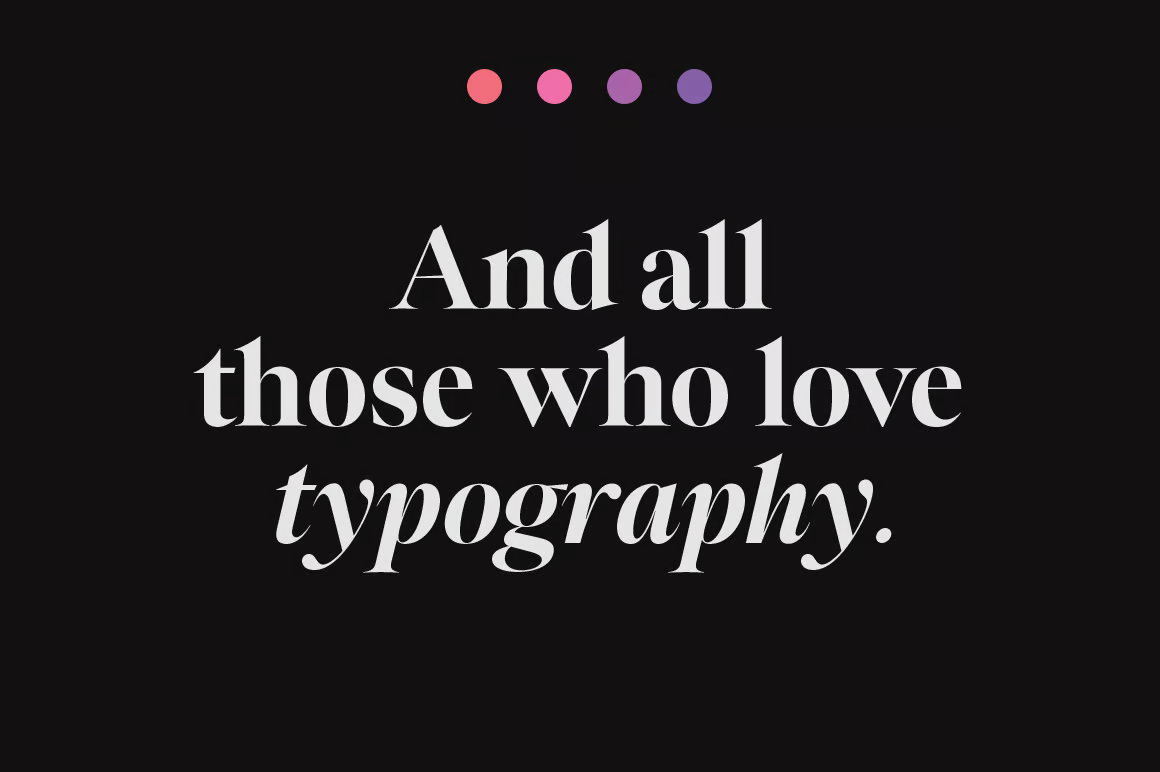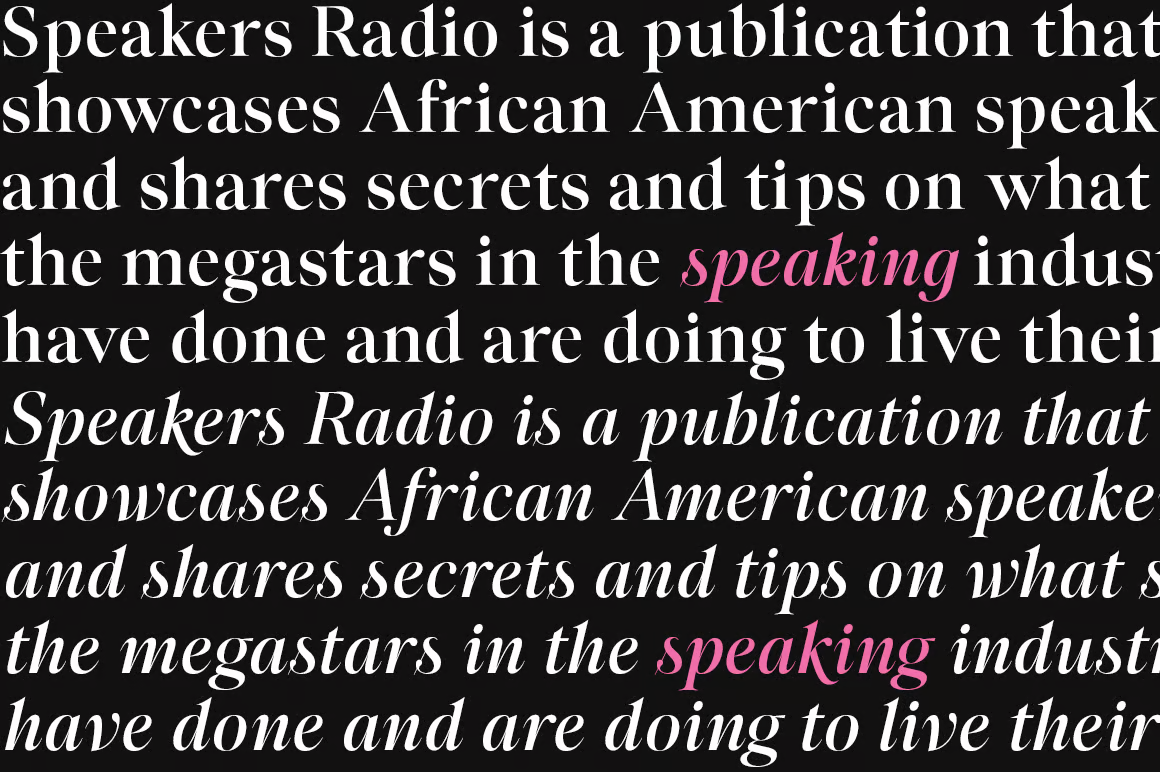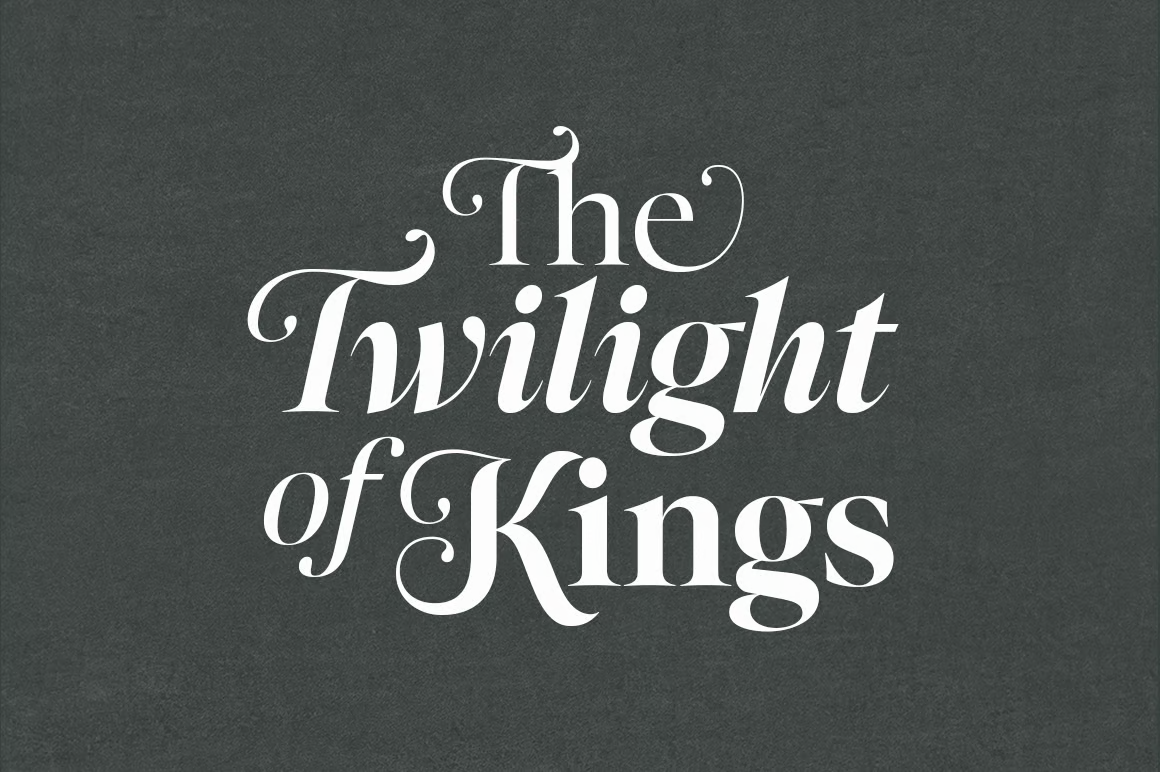
Megafield Font
Description de Megafield Font
Megafield est une police à empattement d’affichage de Greatstudio92 conçue avec des formes omises, presque architecturales, des traits dynamiques, nets et clairs et des empattements à contraste élevé, pointus aux extrémités. Cette police combine les aspects les plus classiques des empattements avec une innovation qui lui permet de transmettre à la fois sophistication et attitude. Megafield est une famille de polices élégante mais affirmée qui comprend un ensemble diversifié de caractères fonctionnels et d’affichage.
La famille Megafield se compose de 12 polices : 6 graisses allant de Light à Extra Bold avec leurs italiques. Ces polices sont idéales pour toutes sortes de designs, que vous souhaitiez ou non donner à votre design un aspect rétro mais cool et sophistiqué. Parfaites pour une utilisation dans les titres, les magazines, les logos, les emballages, les éditoriaux et bien d’autres domaines, Megafield ajoute un aspect professionnel à vos projets. .